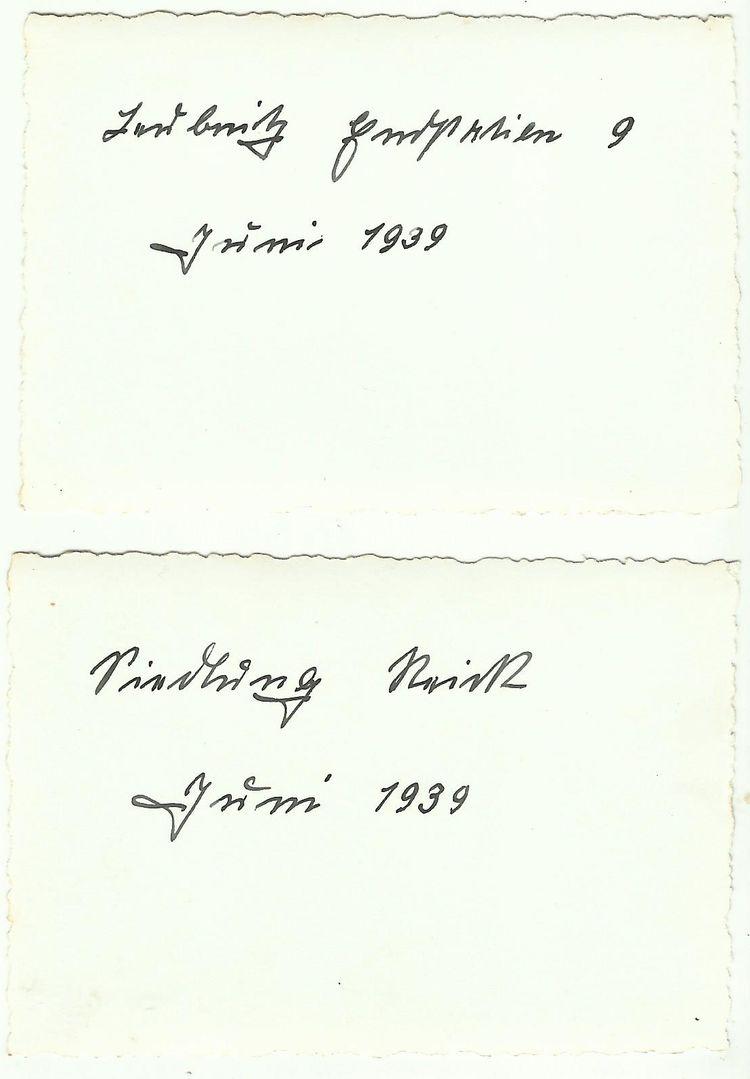
Hab mal wieder ein Problem mit zwei  Sachen beim entziffern der Schrift. Kann jemand wieder helfen.
Siedlung kann lesen.
vielen Dank, langsam lerne ich die Schreibschrift,  kommt auch immer auf die Handschrift desjenigen an.
Das kleine u scheint relativ speziell, mit dem Querstrich darüber, der als so eine Art Kringel aus der Schreibbewegung als Ende eines Aufstrichs ausgeführt ist. Weiß nicht, ob das oft so praktiziert wurde …
Vielen Dank für die Erklärung. Langsam lerne ich die Schreibschrift. Kommt auch auf dem Schreiber an, der es geschrieben hat.
Hier mal die Vorderseite der Fotos.
Siedlung Reick - Heimstätten Genossenschaft Dresden - Reick , wieich jetzt gelesen habe.
Ja, der Kringel gehört immer aufs u.
Schon klar, aber auch immer so wie bei diesem Schreiber praktiziert, also als Aufstrich am Ende des Buchstabens, der dann ohne abzusetzen in einen Kringel überführt wird, welcher statt über dem u rechts daneben/hinter dem Buchstaben landet? War das common practice oder eine Eigenart des Schreibers? Hätte jetzt eher vermutet eine Eigenart des Schreibers, und das im allgemeinen der Strich oder Kringel auf dem u in abgesetzter Schreibbewegung, also ähnlich wie ein i-Punkt, nach Schreiben des eigentlichen Buchstabens über denselben gesetzt wird. Hoffe, ich habe mich verständlich ausgedrückt. Was meinst du?
Der Kringel hat mich auch verwirrt. Das hängt, glaube ich, davon ab, ob man die u-Bögen erst nach der Vollendung des ganzen Wortes schreibt, oder zu jedem Buchstaben einzeln; so wie manche gleich einen Punkt übers i setzen und andere erst, wenn das ganze Wort geschrieben ist. Die Schreiber (die ich kannte), die entweder Kurrent geschrieben haben oder von dieser beim Lateinischen beeinflusst waren, machten meist erst die u-Bögen am Ende des Wortes … aber das heißt ja nix.
Man sprach daher ja auch von einer "ausgeschriebenen Handschrift", die dann kaum noch aus iner sauberen Kurrent oder Latein besteht, sondern aus irgend einer Übergangsform. Manche Buchstaben verändern sich dabei in eibe, in keiner Schul-Schreibschrift vorkomensden Form, so sehe ich in vielen Handschriften, das ein g zu einer Schleife mutiert, und sehr häufige Silben, wie ...heit  ...keit und ...ung abgekürzt werden, z.B. ung zu ng wird, und in weiterer Verkürzung die unterere g-Schleife gleich mit dem rechten Abstrich des n zu einem Ligaturbuchstaben ähnlich einer nj-Ligatur ohne punkt wird. Bekommt man dann in einer Frage nur ein einzelnes Wort eines spezifischen Schreibers zum Entziffern vorgesetzt,ist das kaum möglich. Hat man aber einen längeren Text dieses Schreibers, findet man aus dem Zusammenhang bekannte Worte, weil die deinfach da hin gehören müssen, z.B. typische Grußformeln und Brief-Eröffnungen. Daraus erschließen sich erste Buchstaben die dann andere Worte lesbar machen und aus dem Zusammenhang heraus benachbarte Worte, so dass man sich bald das komplette Alfabet  mit Verkürzungdzeichen desSchreibers erarbeiten kann, bis man all seine Briefe flüssig lesen kann.
Der größte Fehler, den viele Fragesteller machen, die ein einzelnes Wort "übersetzt" haben wollen, ist, nur dieses Wort vorzulegen. Das spezielle u konnte hier nur aus der Logik des Monatsnamens erschlossen werden, was dann der Schlüssel zu den anderen Worten ist.
Hat man aber einen längeren Text dieses Schreibers, findet man aus dem Zusammenhang bekannte Worte, weil die deinfach da hin gehören müssen, z.B. typische Grußformeln und Brief-Eröffnungen. Daraus erschließen sich erste Buchstaben die dann andere Worte lesbar machen und aus dem Zusammenhang heraus benachbarte Worte …
Die Methodik ist glaube ich relativ gängig in der Kryptoanalytik, die mit der Enigma verschlüsselten Nachrichten der deutschen Marine im zweiten Weltkrieg ließen sich letztlich durch einen Wetterbericht knacken, der immer zu ähnlichen Zeiten übersendet wurde und naturgemäß immer ähnliche Worte, typische Wetterberichte halt, enthielt.
Das läuft dann oft sogar ohne groes spezielles Nachdenken im Kopf ab. Da findet man in einem Nachlass einen Feldpost-Brief, bei dem ja relativ klar ist, welcherart Themen in diesem Brief vorkommen werden, Persönliche Ansprachen, ein Mach Dir keine Sorgen, mit geht es gut,und eben Beschreibung von Kriegserlebnissen und Orten. Zzunächst hat man da ein fürchterliches Gekrakel vor sich,von dem man nur Bahnhof versteht, der Redewendung entsprechend. Sobald einem dann dieser Bahnhof ins Auge springt, tauchen weitere erkennbare Worte auf, und nur einige Minuten später liest man den Brief, wie ihn damals auch die Angehörigen gelesen haben.
Mein erstes Erlebnis dieser Art war in der KFZ-Mechaniker Lehre. Mein Ausbildungsbetrieb hatte eine kundenfrundliche Methode der Auftragsweteilung eingeführt. Neben dem Briefschlitz der Auftrags-Annahme hing ein Kasten mit Umschlägen, in die der Kunde seine Autoschlüssel und den den KFZ-Schein einlehen sollte, und auf dem Umschlag den Arbeitsauftrag aufschreiben sollte. Diese Auftrags-Tüte bekam ich dann eben ausgehändigt,um den beschriebenen Fehler am Fahrzeug zu beheben. Auch unser Werkstattmeister konnte mir nicht erklären, was der Kunde  da gemacht haben will. Ich rätselte also an dem Auftrag eine weile herum, bis mir auffiehl, das die Schrift wir so eine typische Doktorschrift aussah, und die waren in der Regel fürchterlich, weil Studenten den Lehrstoff ausden herunter geratterten Vorlesungen ohne Steno gelernt zu haben, irgendwie mitschreiben mussten.
Und so kam ich auf die Idee, wer ist es gewohnt, solche Schrift sicher zu lesen?  Apotheker!
Ich also rüber zur Apotheke, und tatsächlich, der Apotheker hat mir den Auftrag vorlesen können. Und nur aus dem Auto hätte ich lange gebraucht, den Fehler zu finden, dernn der Auftrag beschieb ein gelegentlich auftretendes Problem.
Wohl eher eine Eigenart des Schreibers. Erinnere mich, gelernt zu haben, daß der "Strich", nicht Kringel, über dem  u  immer nach  Vollendung des Wortes  gemacht werden sollte. Die Kurrent sollte ja "fließend", also ohne Absetzen  ausgeführt werden.  Macht sich eigentlich auch  besser. Aber das muß natürlich auch erst mal "Gewohnheit " werden.